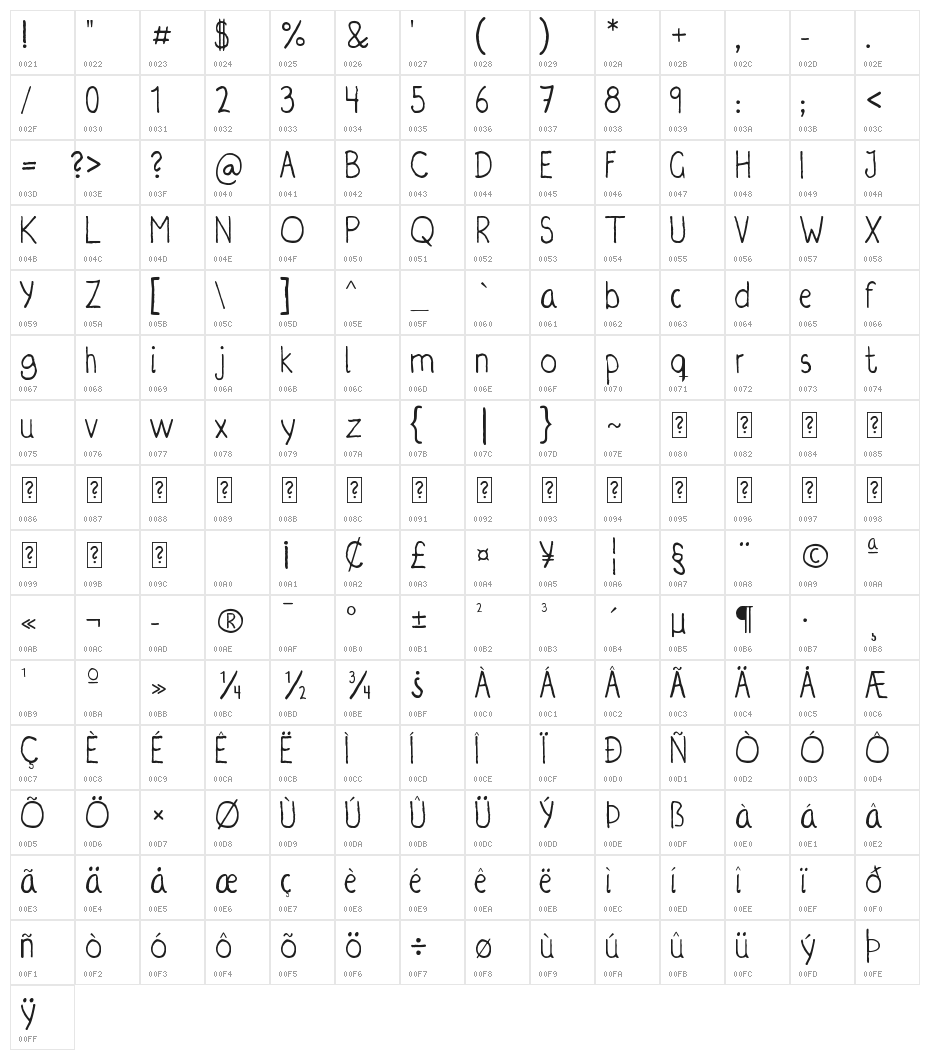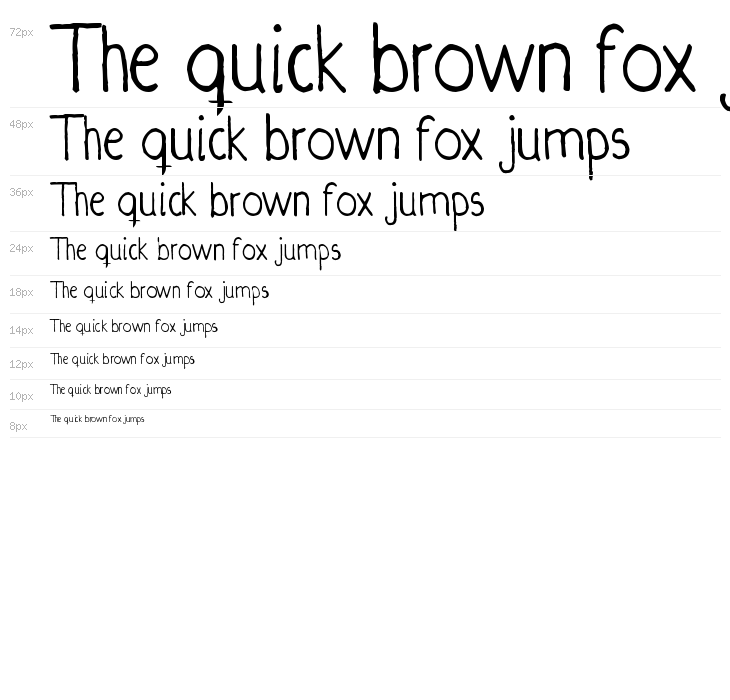
Irregularis Font
| Gesamtstil | Casual, Artistic |
| Anwendungsfall | Headlines, Informal text, Creative projects |
| Vorgeschlagene Projekte | Ideal for children's books, creative posters, greeting cards, and informal branding projects. |